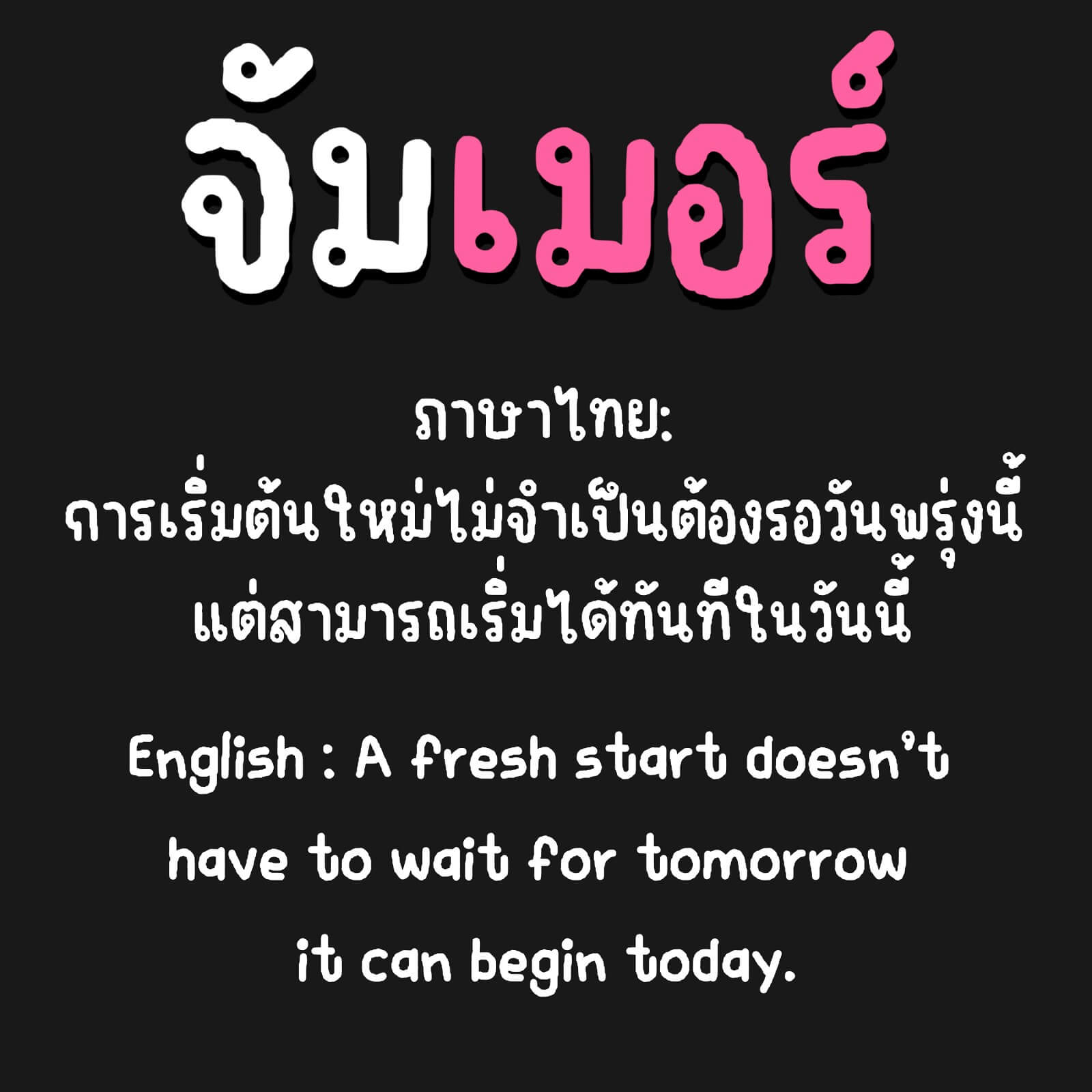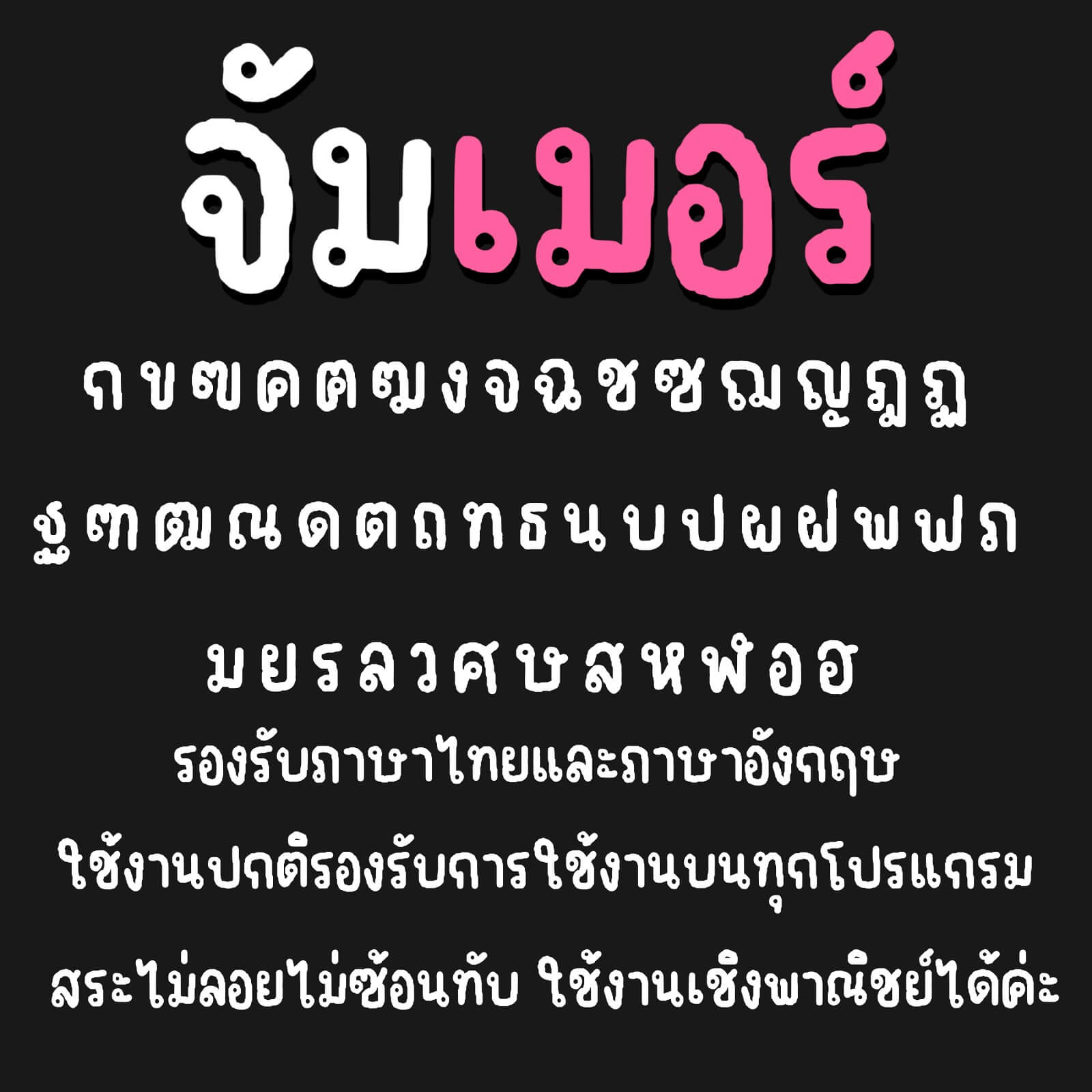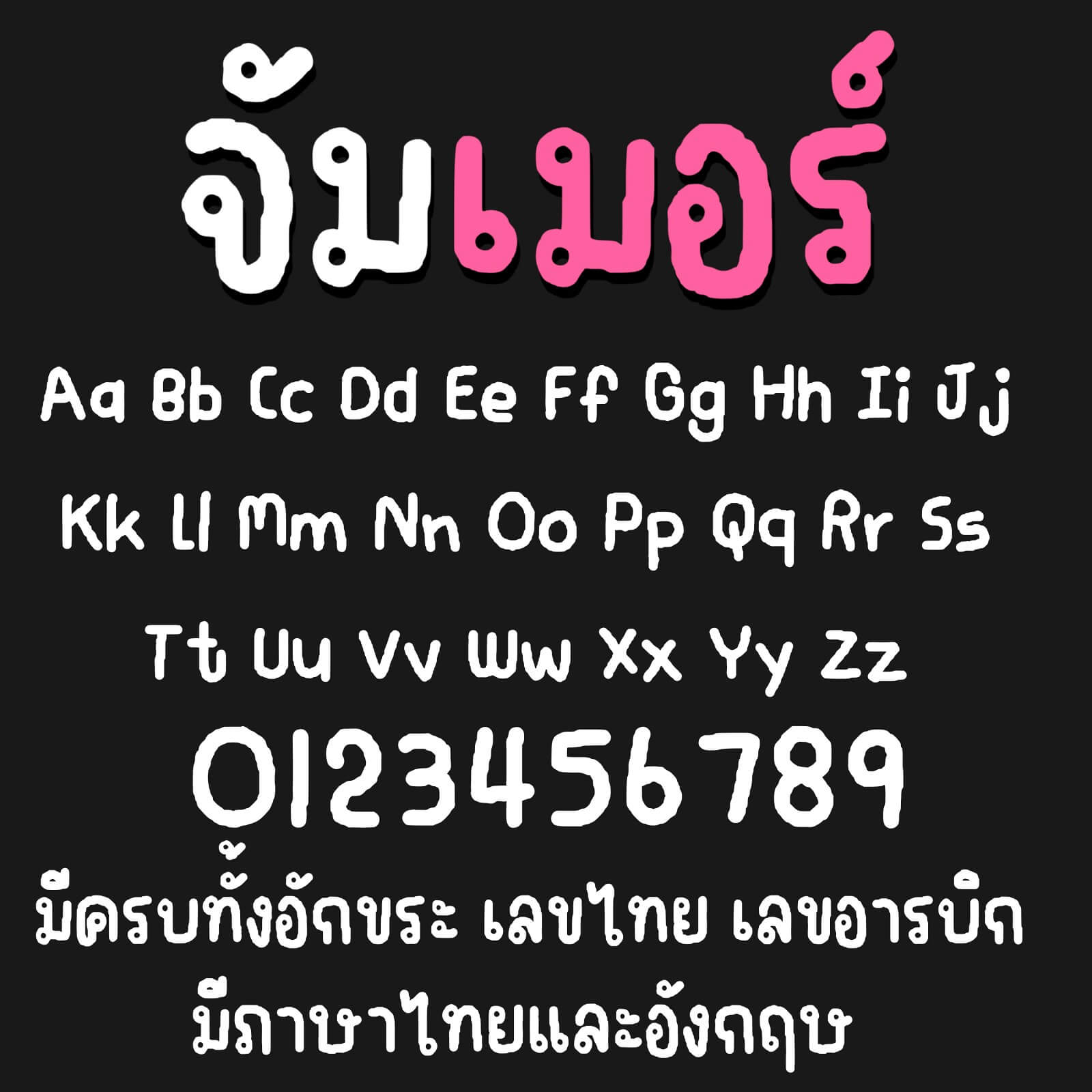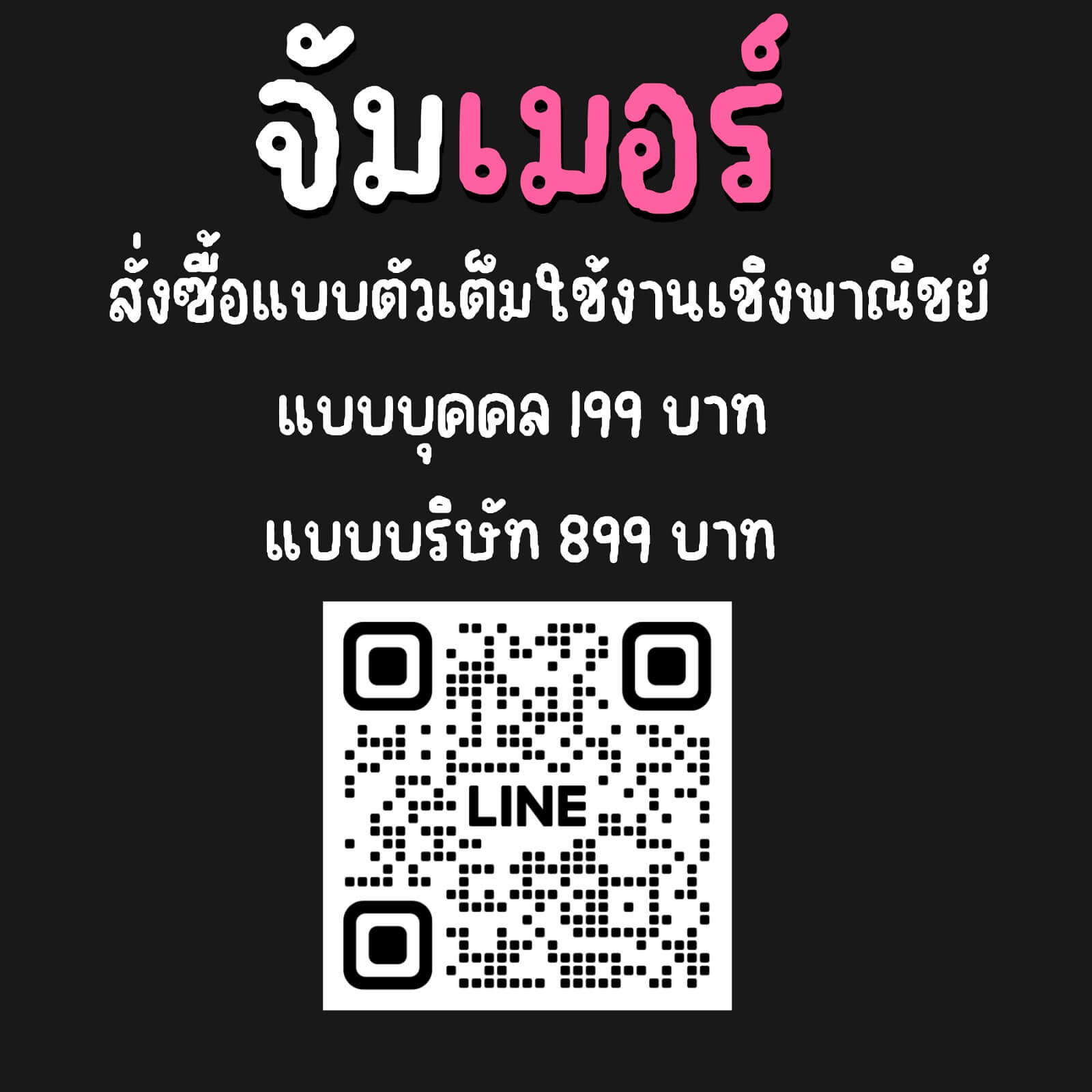
IMTYC อิมจัมเมอร์ ฟอนต์ – นุ่มฟูหยักๆ แต่ยังคงความน่ารักและอ่านง่าย
เหมาะกับทุกสายครีเอเตอร์ ไม่ว่าจะใช้ทำป้าย ข้อความ โพสต์ หรือคอนเทนต์น่ารักๆ
- อักษรผสมตัวโปร่ง
อิมจัมเมอร์ (IMTYC Jammer)